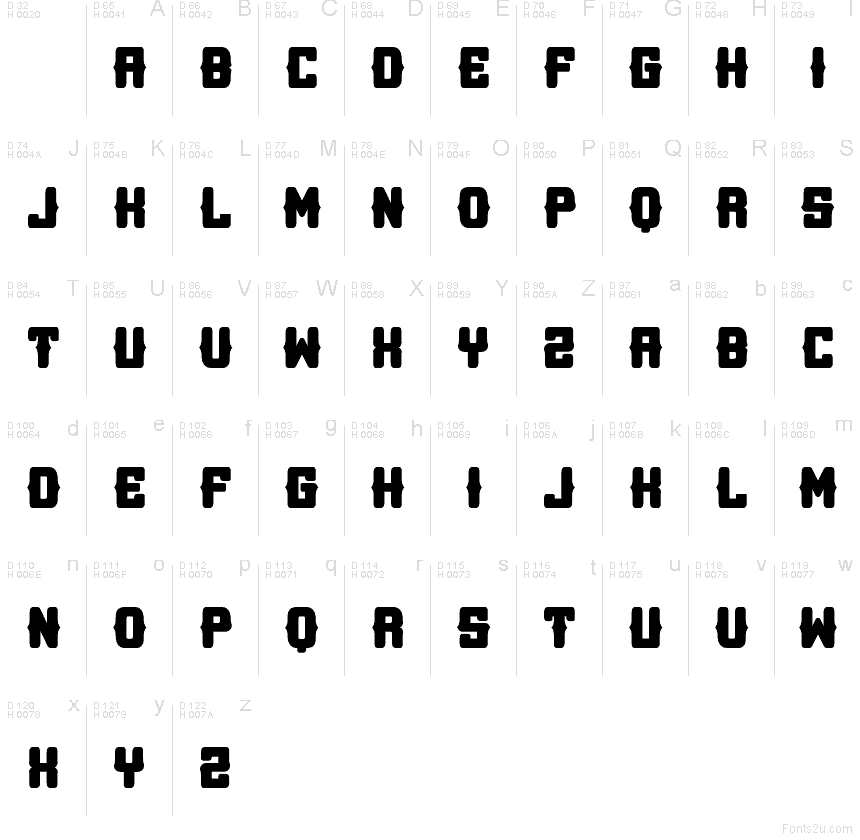
Sombrero Book autorstwa Vladimira Nikolicia to darmowy krój pisma typu display w meksykańskim stylu, definiowany przez szerokie, pionowe sylwetki, które wyglądają jak wycięte z solidnych plakatów. Głęboko zaokrąglone rogi i wklęśnięcia nadają literom rytmicznego, skocznego charakteru, nadając im świątecznego klimatu ręcznie malowanych szyldów, bez nadmiernego przeładowania ozdobnikami.
Ta zwarta konstrukcja świetnie sprawdza się w menu restauracji, brandingu food trucków, ulotkach na fiesty, opakowaniach produktów czy szyldach sklepowych, gdzie krótkie słowa mają pełnić silną funkcję dekoracyjną. Wygięte wcięcia sprawiają, że formy są wystarczająco żywe dla nagłówków i etykiet tematycznych, szczególnie w projektach, które potrzebują wyraźnego akcentu inspirowanego kulturą łacińską, a nie neutralnego kroju display.